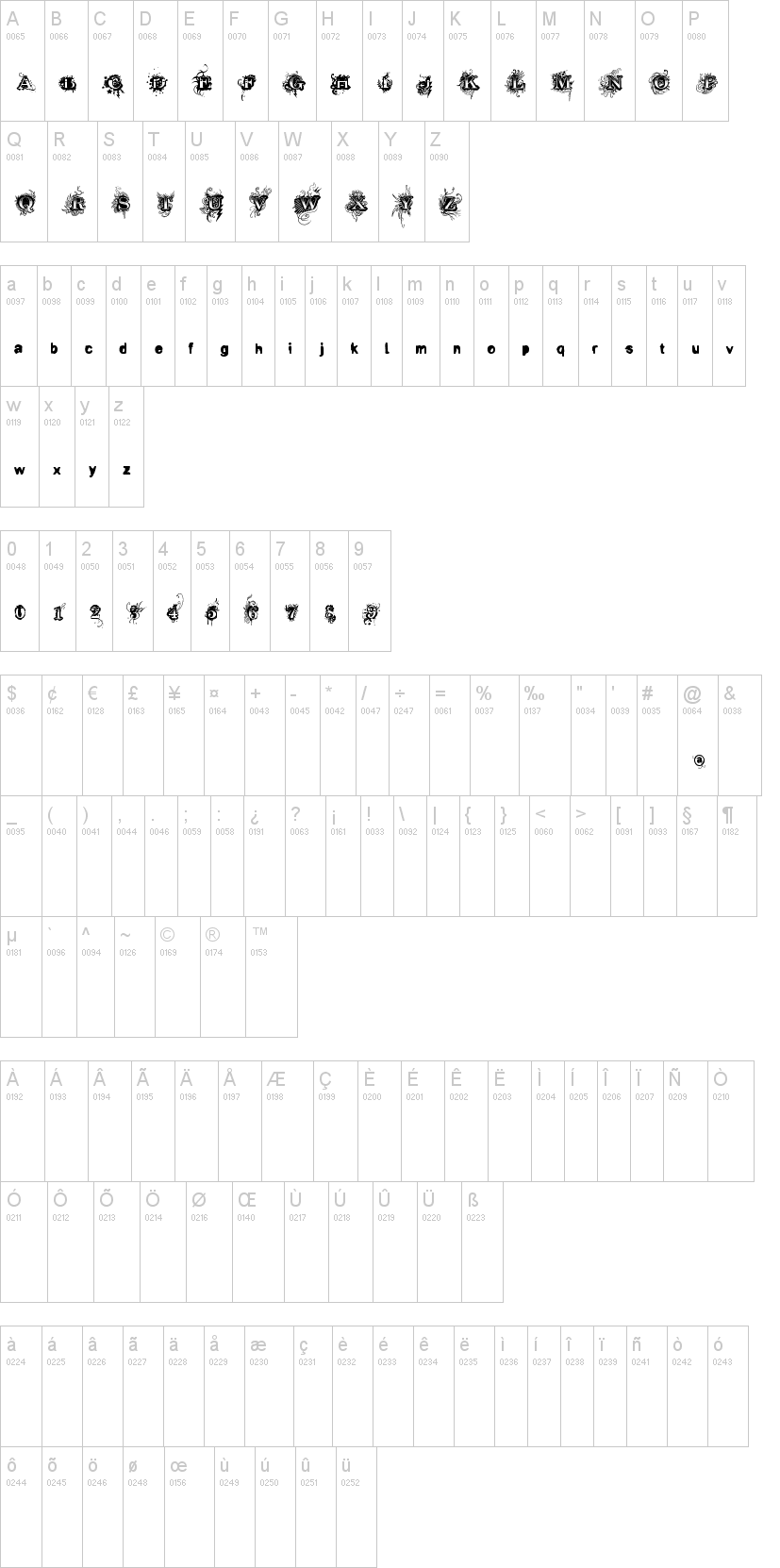
? Vtks Revolt 是一款拥有独特复古风格的英文字体,它由葡萄牙设计师Vitor Marques所设计。Vtks Revolt 字体以其特有的复古风格,给人以活泼和激情的感觉,非常适合用于商业广告、海报、品牌标识等设计中。它具有良好的可读性,可以满足大多数设计需求。内容介绍
Vtks Revolt是一款非常不错的手写艺术字体,具有很好的视觉感,适合于文化类的宣传设计、商业类品牌的广告和产品包装设计以及个性化文字排版等较多场景。